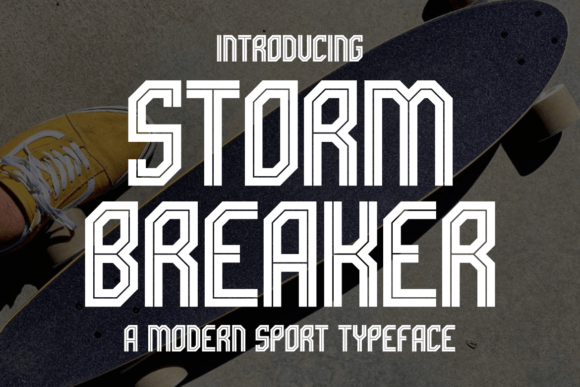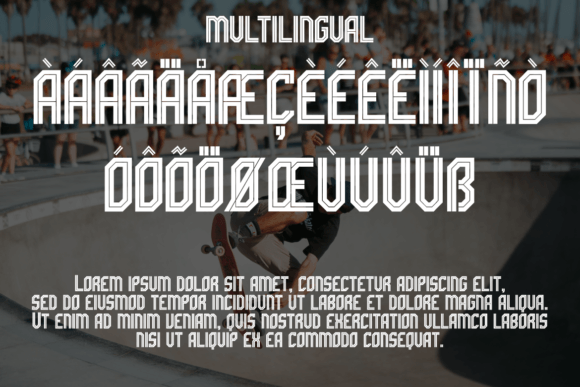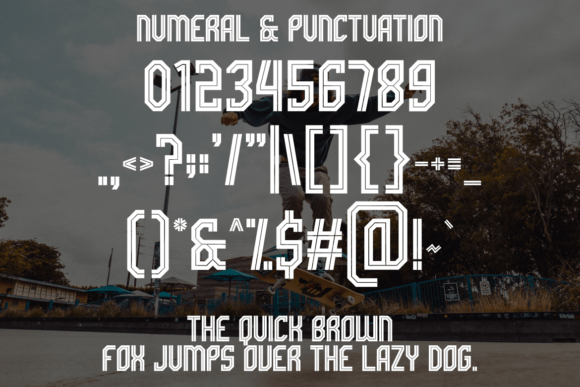
فونت Storm Breaker انگلیسی
| ⭐ توضیحات | معرفی محصول جدید **STORM BREAKER** – فونت مدرن
** STORM BREAKER ** – فونت مدرن یک فونت نمایشگر برجسته و معتبر است. این فونت برای هر پروژه برندسازی مانند لوگو، طراحی قالب، esport و بسیاری موارد دیگر مناسب است. برجسته در طیف گسترده ای از زمینه ها. |